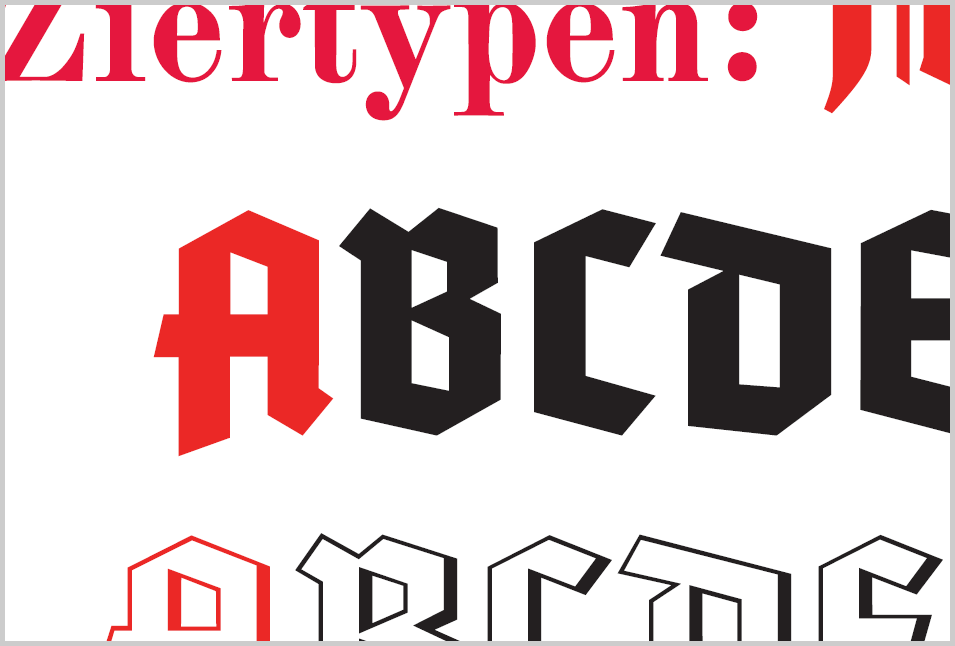
Es geht mehrheitlich um die Historie eines Designs und dass Böhmermann mal wieder ein Ferkelchen durchs Dorf treibt:
Faszinierend übrigens, wie die "gut vorbereitet" interpretieren. Die Schlange keinesfalls aus der griechischen Mythologie, sie ist Bestandteil sehr, sehr vieler mythischer Erzählungen in vielen Völkern, geradezu global (was für christliche Leitkulturfans: https://de.wikipedia.org/wiki/Eherne_Schlange, für alle anderen: ein Überbleibsel matriarchalischer/weiblicher Kulte, die die Häutung der Schlange als Symbol für Wiedergeburt einer Erdgöttin sahen).
Wichtigster Punkt meiner Meinung nach ist, dass es sich weniger um ein Logo handelt als um ein Hinweisschild. Und, was ich nicht kannte, ein interessanter Verweis auf das österreichische Apotheken-A (Beispiel hier bei der Apothekerkammer), welches mir persönlich ein büschen zu unwuchtig ist.
Ich fand die animierten, grün leuchtenden Kreuze in Frankreich schon in den 90ern cooler, als es sich noch um Neonröhren gehandelt hat und nicht LED, als unser rotes Apotheken-A. Könnte man meiner Meinung nach gerne übernehmen. (Die drei Löffel bitte nicht.) 🙂
Ich nehme an, dass das A nicht eins zu eins einer Schaftstiefelgrotesk entnommen ist, aber welche kommt am nächsten dran? 🤔
Kreuze sind problematisch. Sie sind ideologisch ziemlich aufgeladen und zudem bereits Marken-/Kenn/Hinweiszeichen anderer Organisationen. ℞ kennt hier so gut wie keiner. Vielleicht ein A aus der Akzidenz-Grotesk, um mal den Thread von der Berthold-Übernahme aufzugreifen? Oder einfach das A aus der Optima oder Publica nehmen... Oder, ganz verwegen, ein kleines kursives a aus der Rotis Semi Sans. Ich denke, ein A/a und Rot auf Weiß sollte schon der Kontinuität halber fürs Erste beibehalten werden.
Sie sind ideologisch ziemlich aufgeladen und zudem bereits Marken-/Kenn/Hinweiszeichen anderer Organisationen.
Ich sehe da weniger Probleme … das Kreuz ist im medizinischen Bereich ja bereits sehr verbreitet. Die Abbildung zeigt übrigens ein Verkehrsschild.
An ℞ gefällt mir nicht, dass es wieder ein Buchstabe ist.
Ein Kreuz ist auch schon schon auf so ziemlich jedem Verbandkasten drauf. Ich denke, dass sich die Verwirrung in Grenzen hielte, wenn man das grüne Kreuz übernehmen würde. Es steht ja auch selten für sich allein, sondern zusammen mit dem Apotheken-Namen, meistens in der Form X-Apotheke. (Es könnte ja auch erlaubt sein, für Y Jahre beide Kennzeichnungen parallel zu führen?)
Ich denke, das IRK und das DRK hätten damit ein großes Problem der Verwässerung ihrer Markenidentität, zudem steht das Symbol auch für Erste Hilfe, etwas, was ein Apotheken-Mensch leisten kann, aber nicht dessen Hauptmerkmal ist. Außerdem bleibt es ein Kreuz, ein in diesen Breiten letztlich christlich okkupiertes Symbol (s. Internationale Schutzzeichen und überhaupt als Zeichen der Rotkreuz-Bewegung inklusiver gesetzlicher Schutzbestimmungen, im Übrigen ein weiteres Ausschlussmerkmal für Apotheken).
Wenn es schon ein neues Identifikationssymbol für Apotheken geben sollte, dann eines, das auch kulturübergreifend funktioniert. Das isländische Symbol rockt 🙂
Ich denke, das IRK und das DRK hätten damit ein großes Problem der Verwässerung ihrer Markenidentität, zudem steht das Symbol auch für Erste Hilfe, etwas, was ein Apotheken-Mensch leisten kann, aber nicht dessen Hauptmerkmal ist.
Ich glaube DRK und IRK sind in Bezug auf ihre Markenindentität nicht ganz so rigoros wie internationale Konzerne die sofort finanzielle Einbußen auf sich zukommen sehen. Und »Erste Hilfe« ist ein recht universeller Begriff für »Hilfe im Notfall« – das kann ein Pflaster, ein verschreibungspflichtiges Medikament oder eben die stabile Seitenlage sein.
Aber wir drehen uns im Kreis. Letztendlich sind quasi alle einfachen Symbole mehrfach belegt – »A« steht für Apotheke, für Fahranfänger oder eben auch für Adobe (um den Kreis zu schließen).
DRK und IRK sind in Bezug auf ihre Markenindentität nicht ganz so rigoros wie internationale Konzerne
Bis auf Disney hat es meines Wissens kein Konzern geschafft, seine wie auch immer gearteten Schutzbedürfnisse in (internationales) Recht zu gießen:
Screenshot der fetten National in der Schriftmappe von Dipl.-Ing. Gerhard Helzel, http://www.romana-hamburg.de/Schriftmappe.pdf. Die rote Hervorhebung des A war passenderweise schon vorhanden. 🙂
Ist dieser Anstrich (Abstrich? Habe nie mit einer Feder geschrieben und meinem Füller ist das egal) unten links nicht reichlich ungewöhnlich für geschriebene Gebrochene?